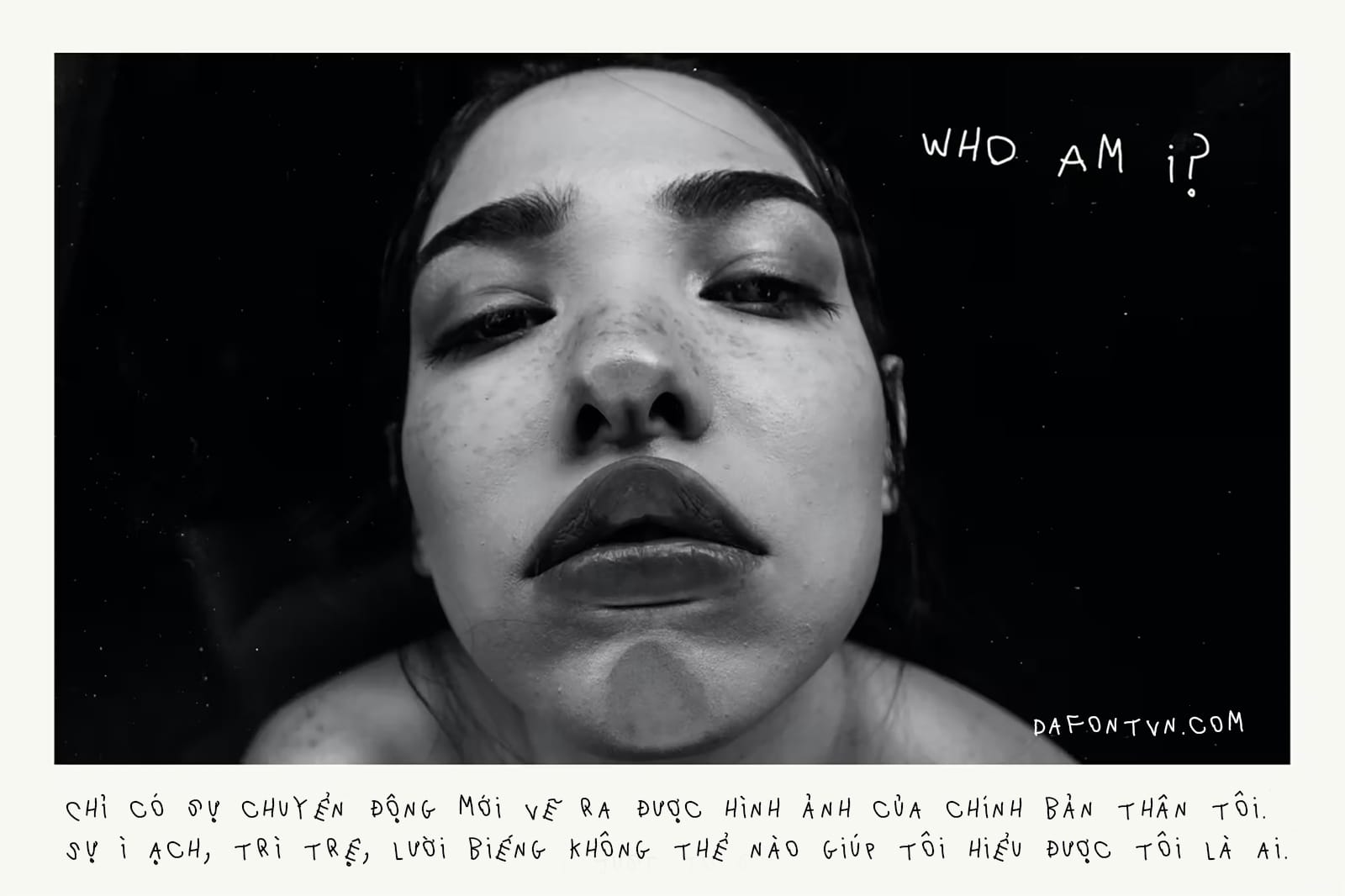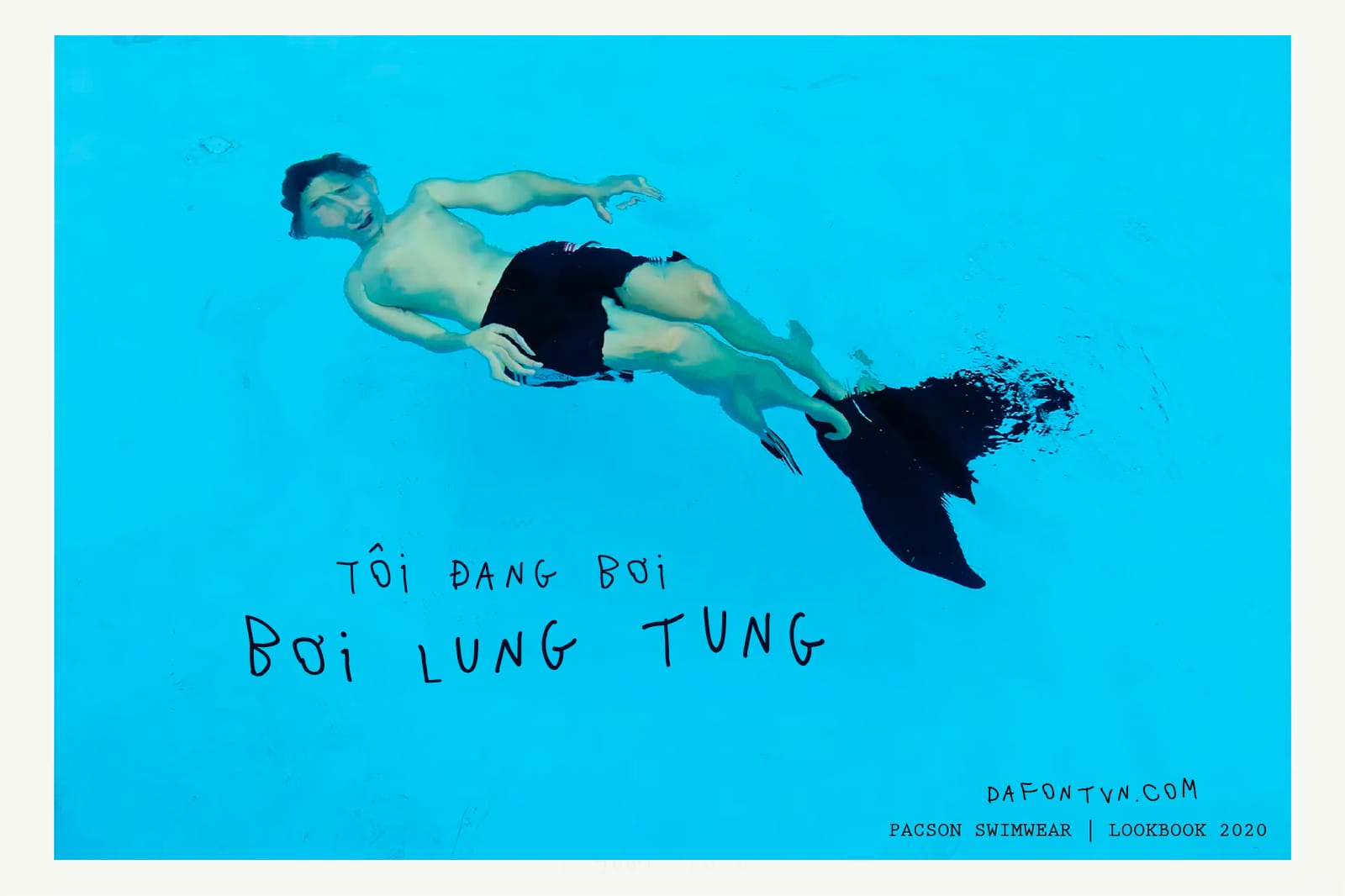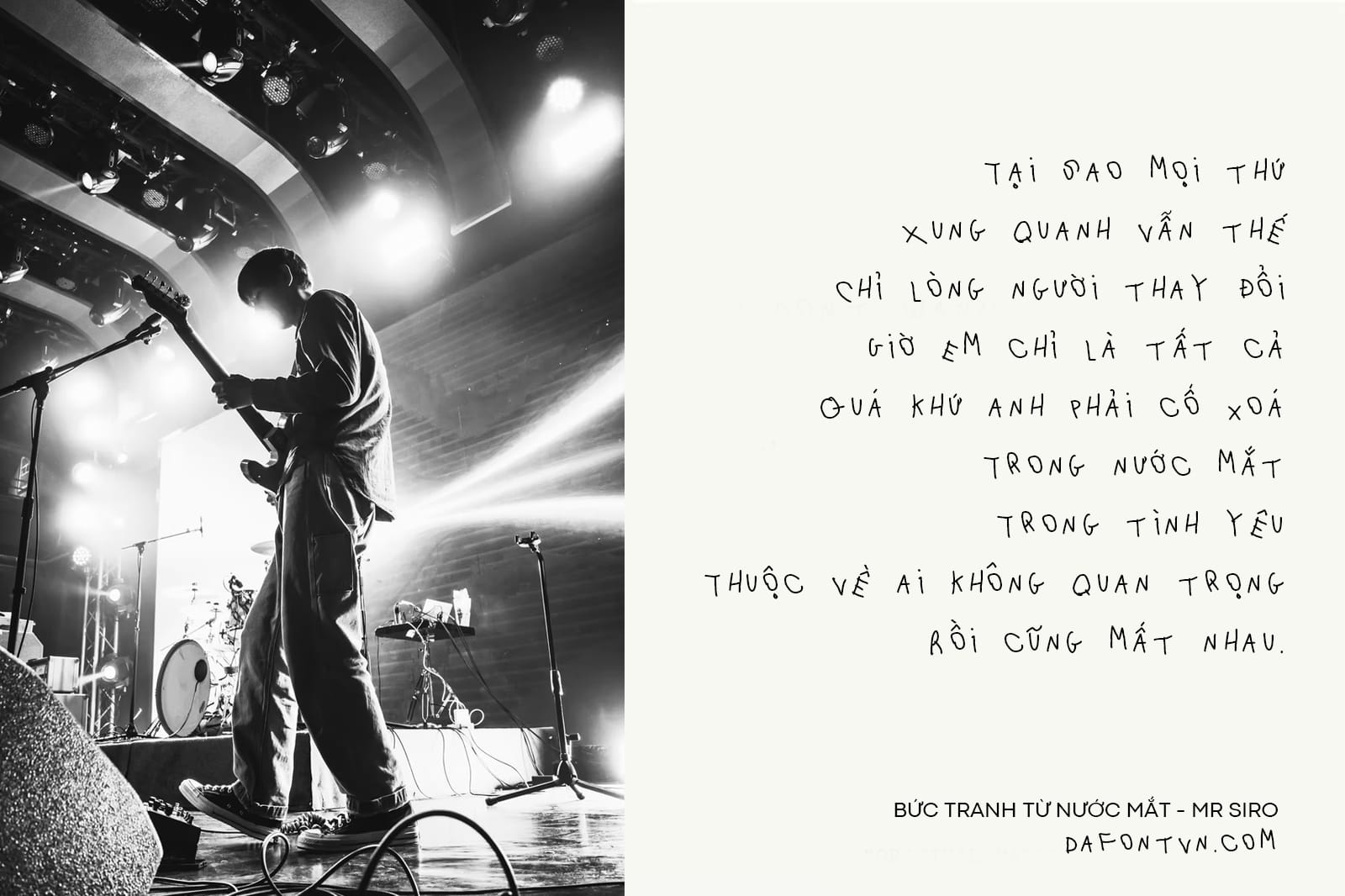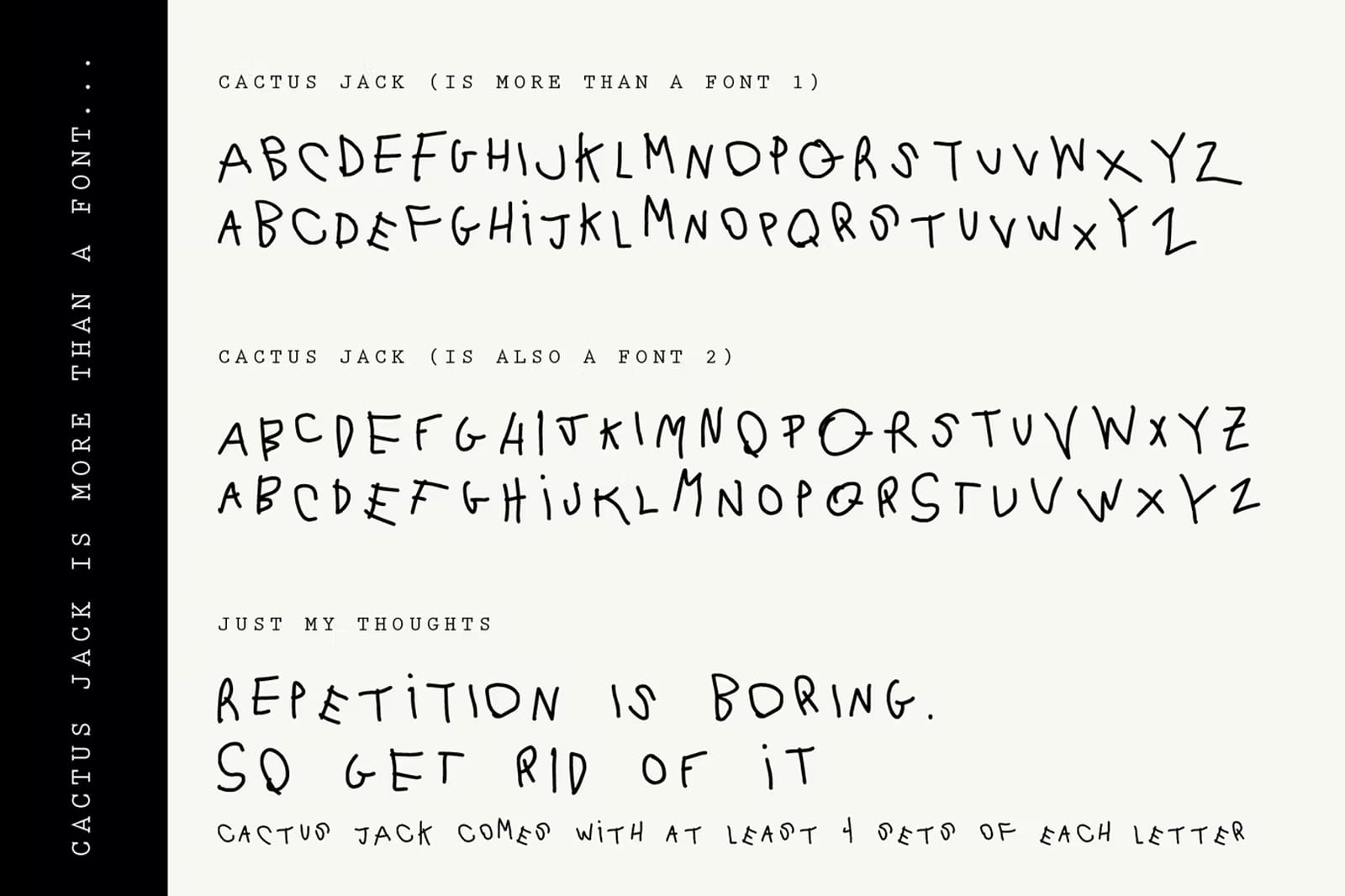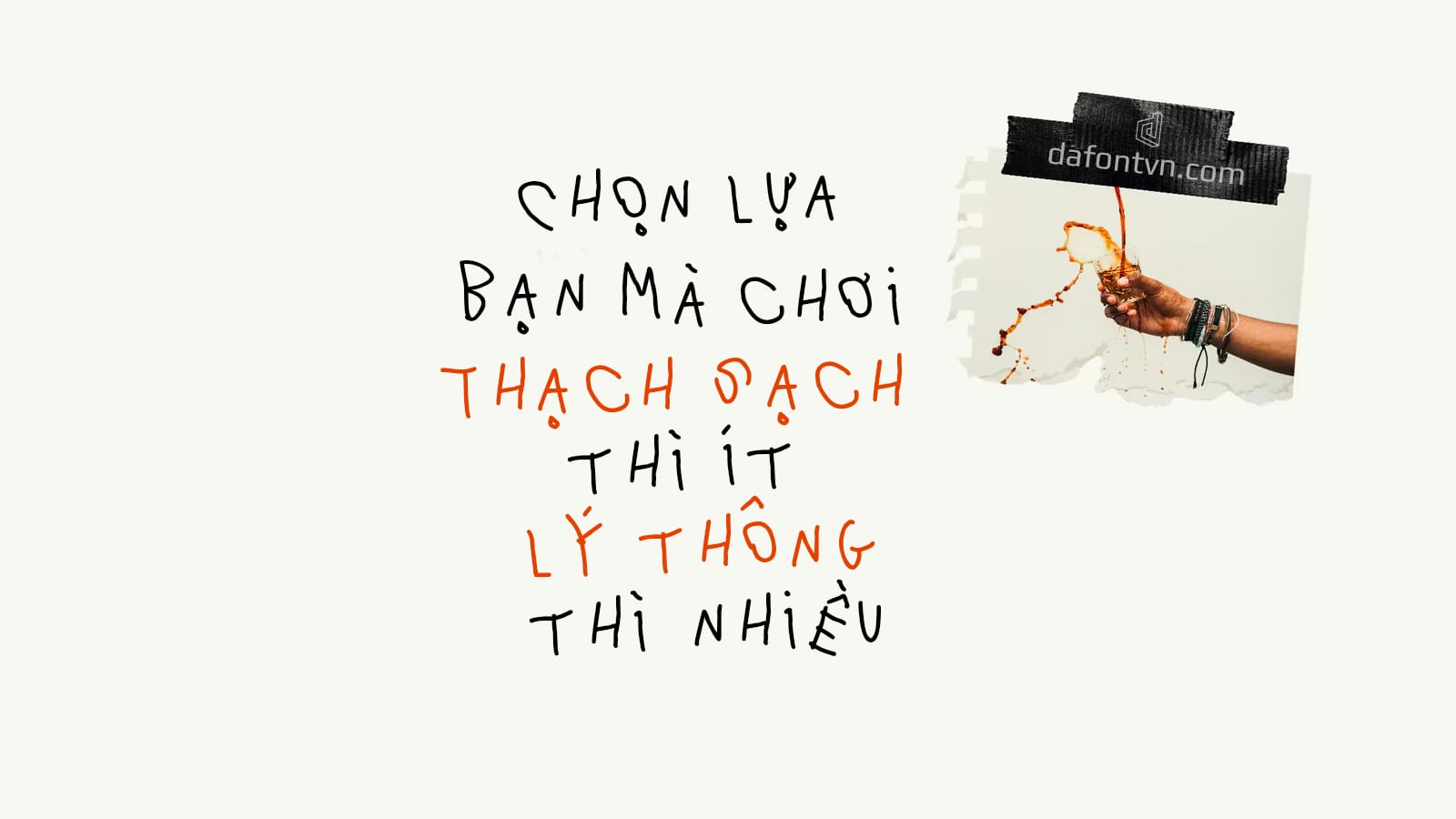
Cactus Jack không chỉ là một phông chữ. Đó là một kiểu font cảm xúc với các nét vẽ được thiết kế nguệch ngoạc mang đến một cái nhìn về cuộc sống, phông chữ mang phong cách mạnh mẽ và kỳ lạ này phù hợp với những thiết kế phá cách và cần 1 thứ gì đó đặc biệt.
Font Cactus Jack Việt Hóa bao gồm hơn 125 biến thể ký tự thông thường, từ ký tự thường và ký tự viết hoa có đôi chút khác nhau.
Font Cactus Jack Việt Hóa bởi DafontVN, kerning, tối ưu và chỉnh sửa lại đôi chút.